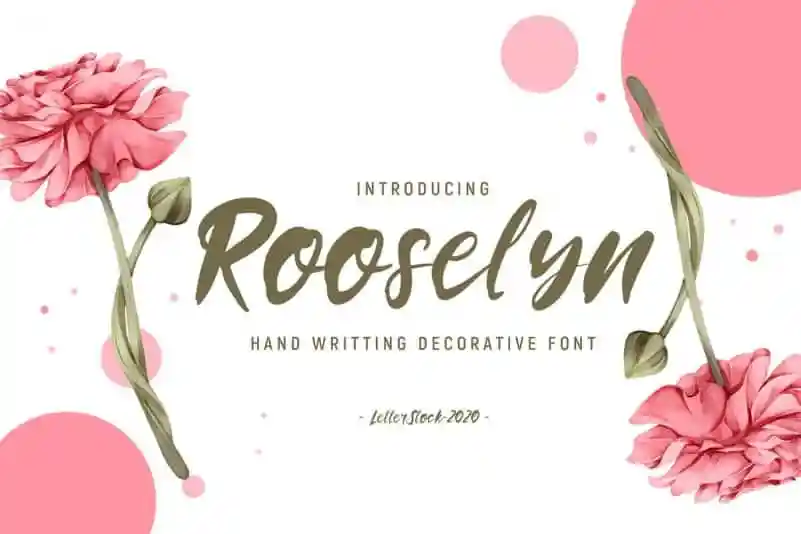
Rooselyn Brush Font – Fonte Grátis
Rooselyn Brush Font
A Rooselyn Brush Font é uma elegante fonte script que traz um toque moderno e sofisticado às suas criações digitais. Inspirada no belíssimo traço de tinta com forma natural encontrada em cartões de convite de casamento, a designer 1001fonts transformou essa inspiração em uma fonte versátil para diversos usos. Esta fonte é ideal tanto para logotipos quanto para materiais gráficos publicitários, como flyers e embalagens. Suas linhas arredondadas e traços naturais garantem um toque delicado, perfeito para aplicação em produtos de moda, roupas e acessórios. A Rooselyn Brush Font é uma ótima escolha para designers que desejam adicionar charme e elegância a seus projetos, sem deixar de lado a praticidade da fonte digital. Com o seu design original, ela irá tornar seu trabalho ainda mais único e pessoal.